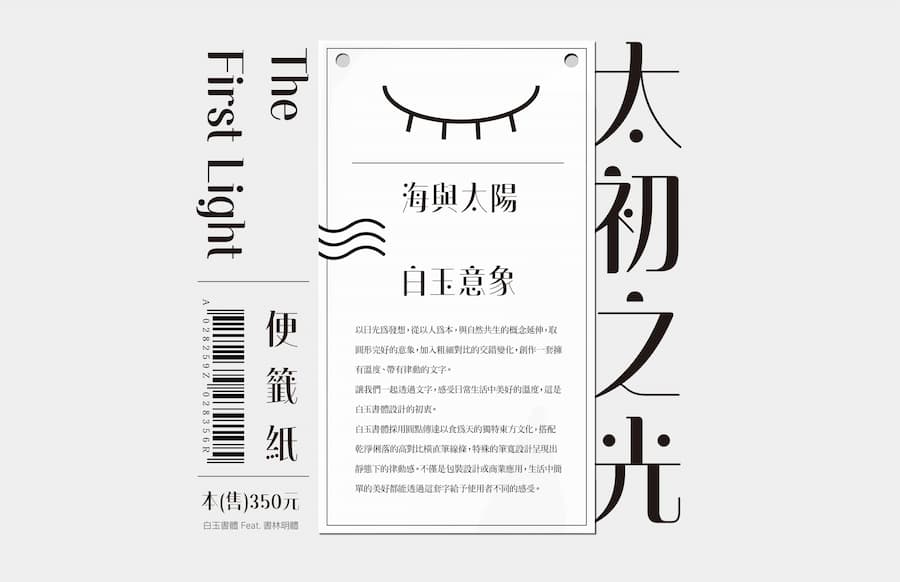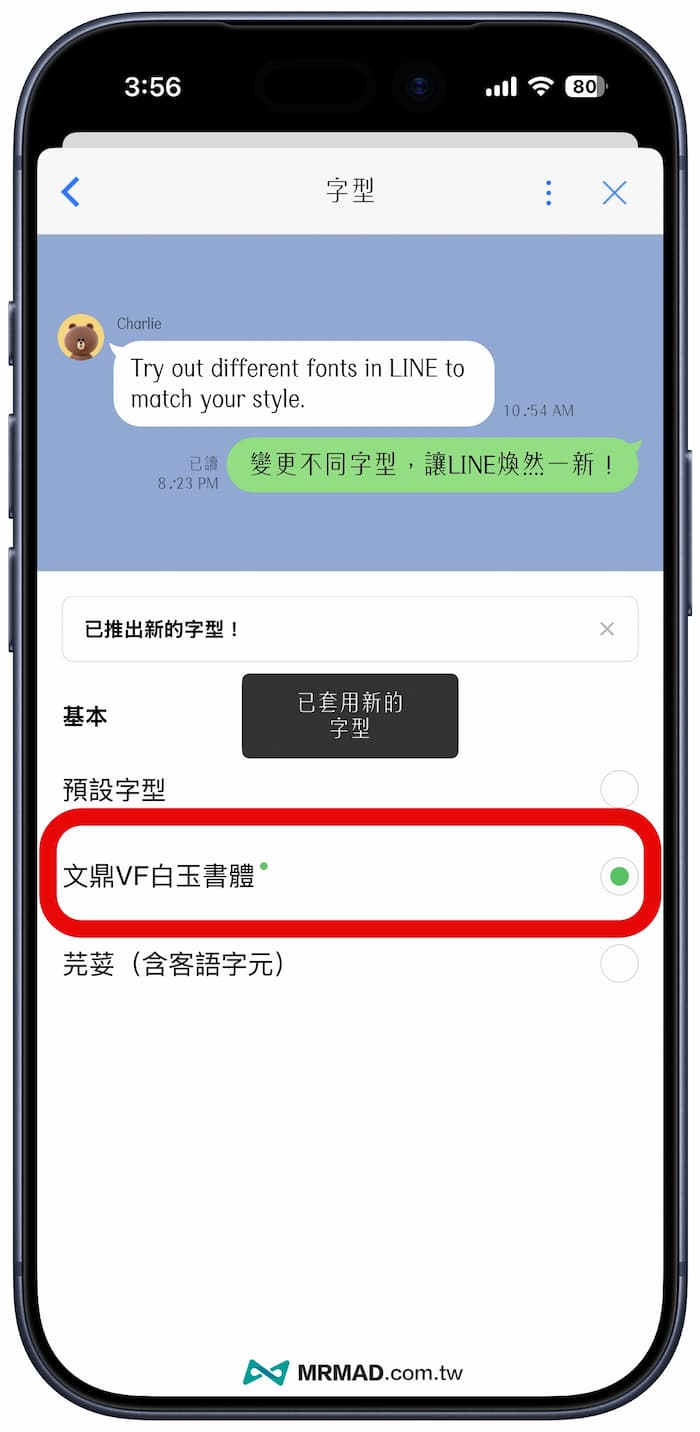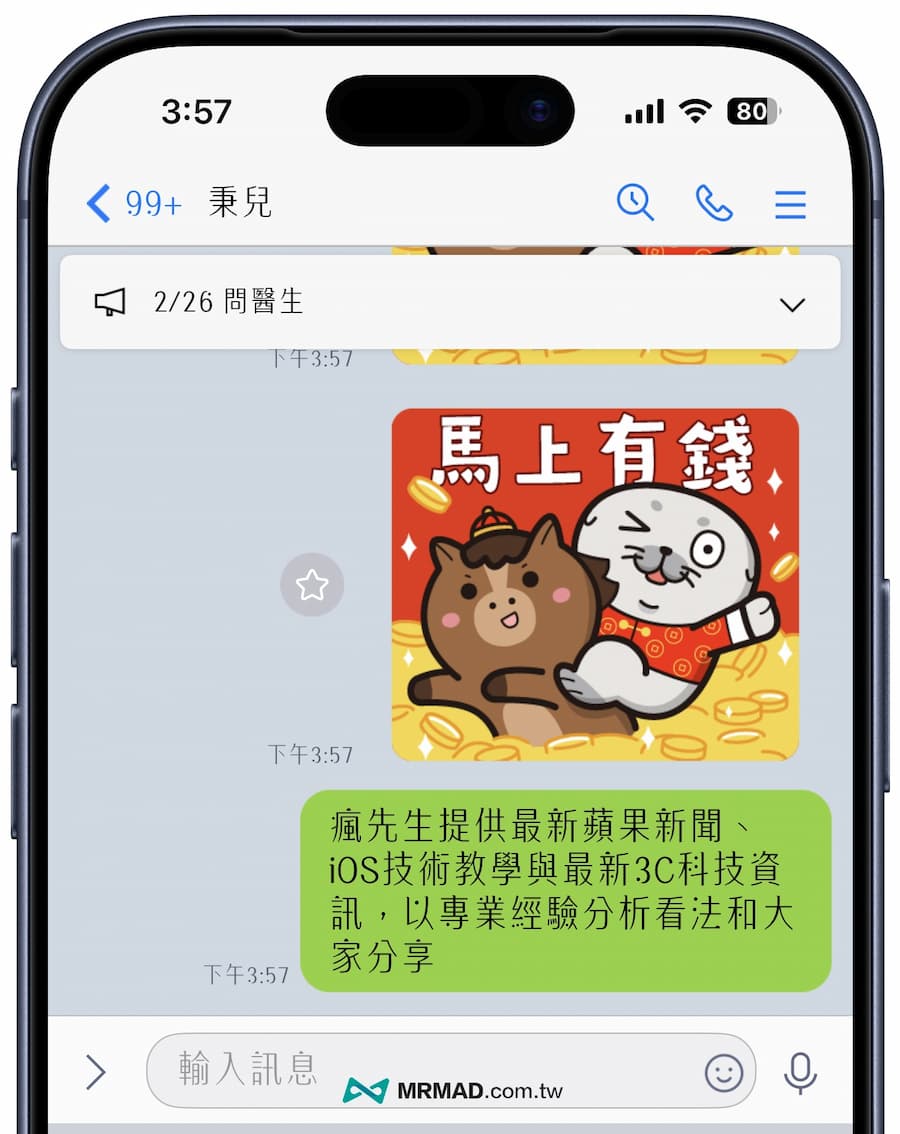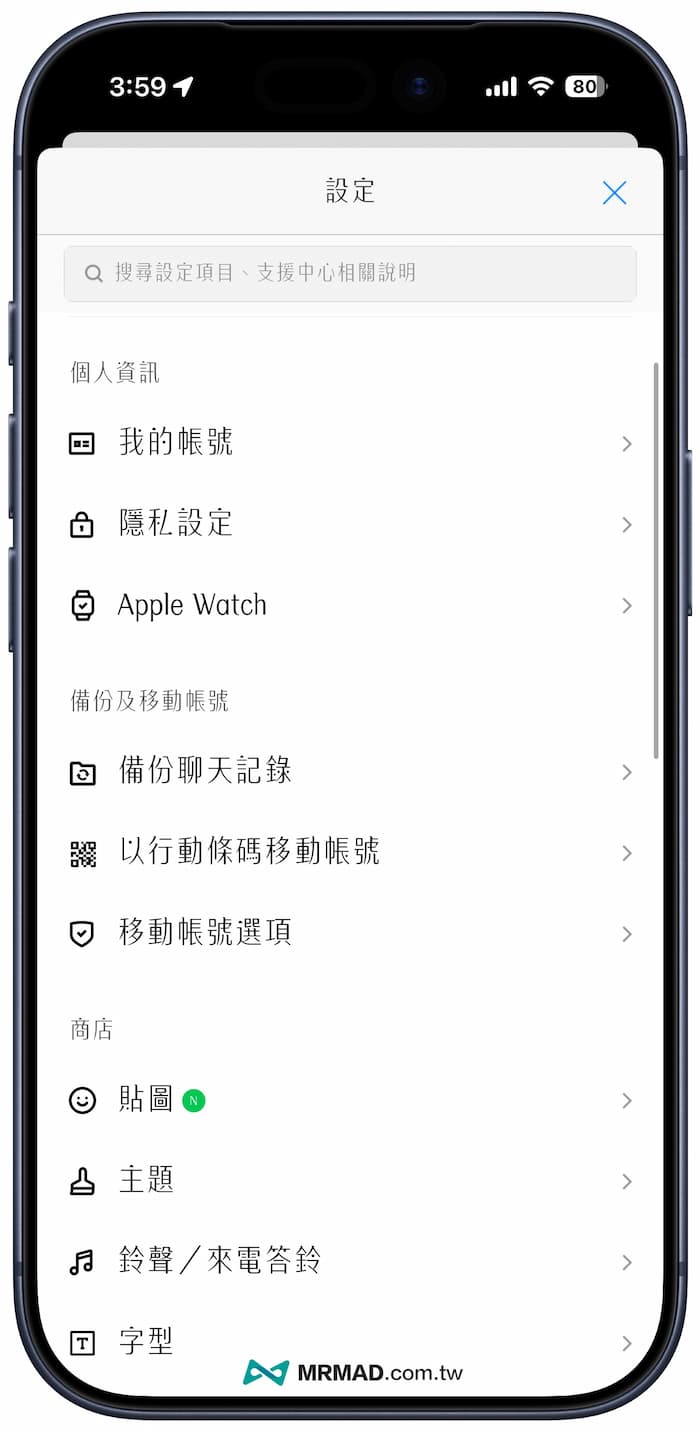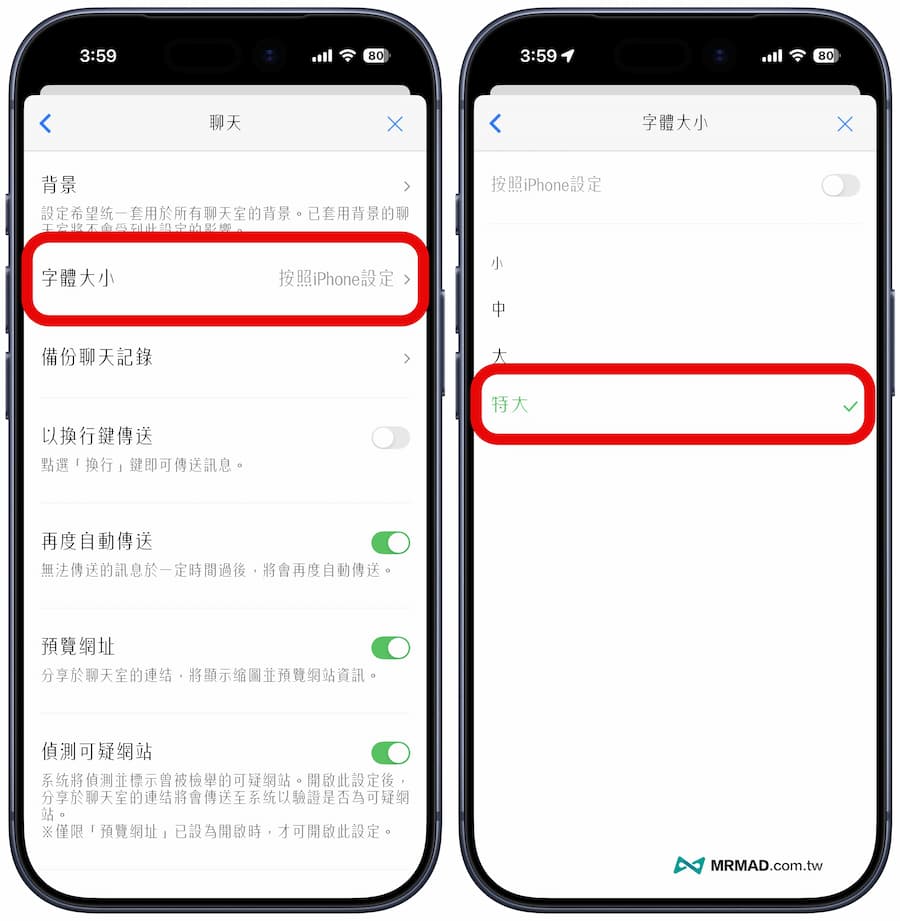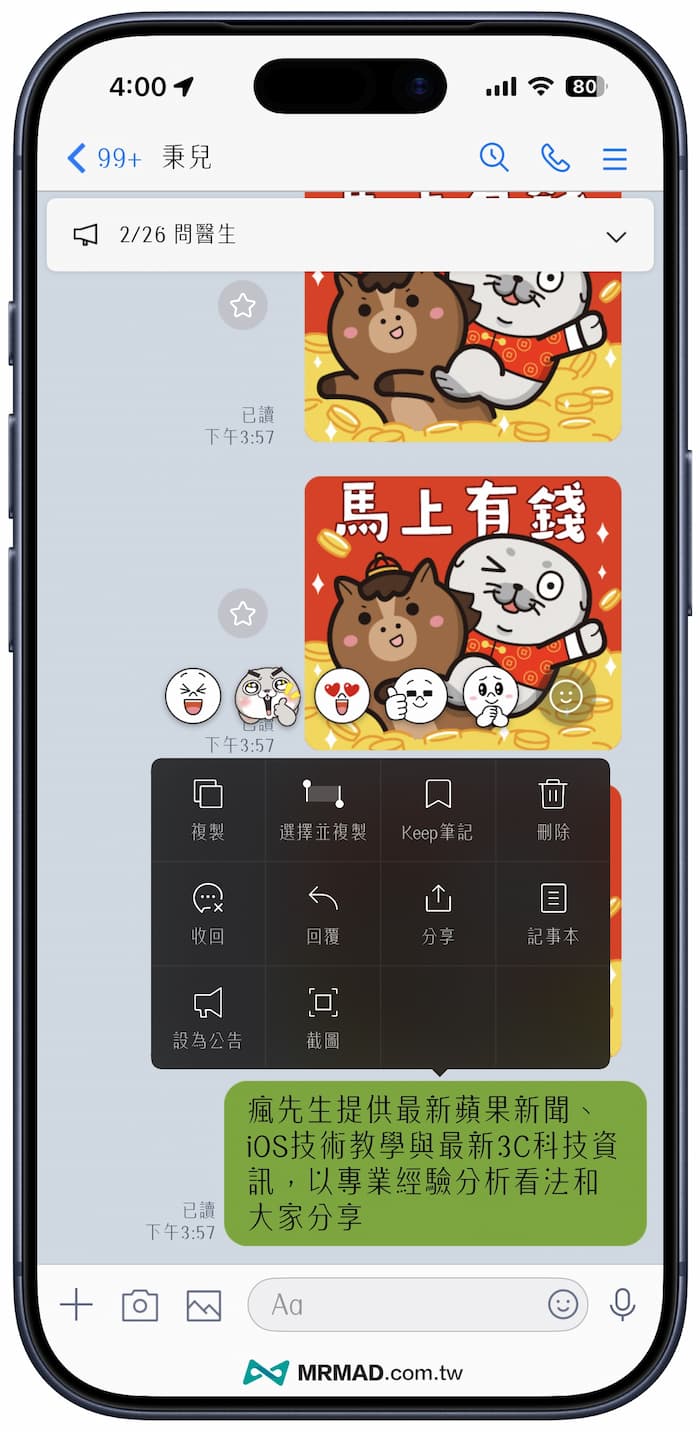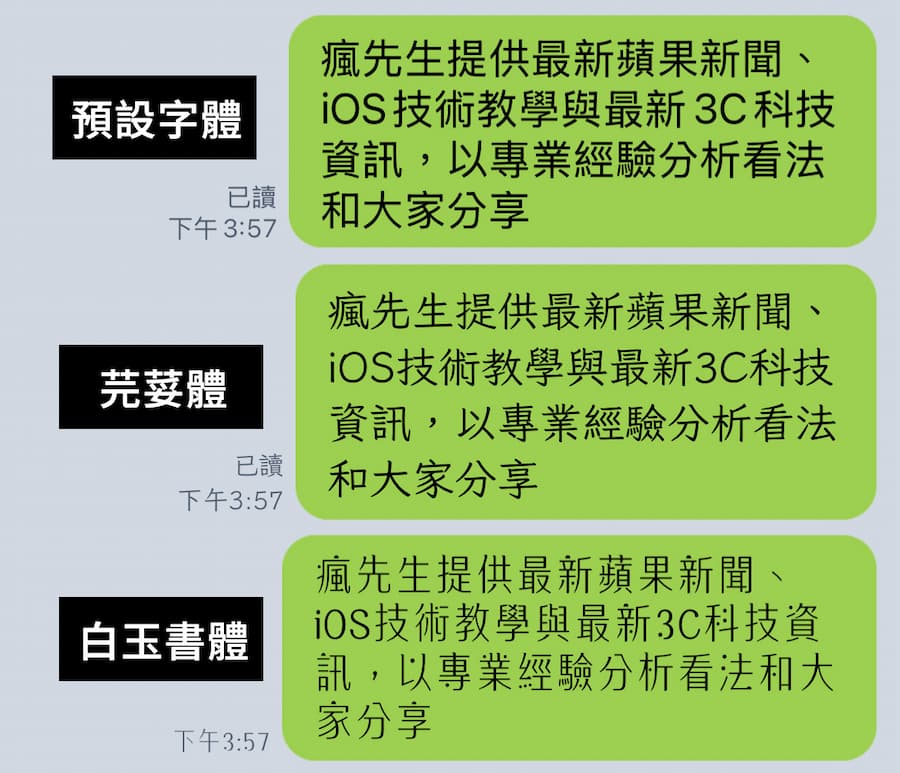
每天都在用的 LINE,看膩了預設字體嗎?LINE 官方近期在手機版悄悄釋出了第三款免費字型「文鼎白玉書體」!這款字體帶有濃濃的文青感與圓潤氣息,一推出就在 Threads 等社群引發網友熱烈討論,本文就來分享 LINE白玉書字體下載套用方法,讓你的 LINE 聊天室也能煥然一新!
LINE白玉書字體長怎樣?與預設LINE字型和芫荽體比較
目前 LINE 手機版內建共提供三種字型讓用戶自由切換,這次新增的白玉書體到底與預設和芫荽體有什麼不同?主要差異如下:
• 系統預設字體: 中規中矩,辨識度最高,適合所有情境與長輩使用。
• 芫荽體: 帶有手寫的溫度感,字跡端正優雅,是前一波爆紅的字體。
• 文鼎白玉書體: 這次的主角!字體整體偏細,筆畫橫直對比明顯,帶點圓潤的可愛感,風格非常清新文青。
白玉書字型設計理念是什麼?
「文鼎白玉書體」是由知名的文鼎字型公司操刀設計,主要是日光為發想,結合了以人為本、與自然共生的理念。
如仔細觀察它的筆畫,會發現它橫筆圓潤、直筆帶有線條修飾,而點的筆畫則是可愛的正圓形,這種高對比的粗細變化,讓文字在靜態中帶有一種律動感,替冰冷的手機螢幕注入了東方人文的溫暖氣息。
放大後的白玉書體不僅保留了圓潤的美感,還能大幅降低閱讀負擔,完美兼顧美觀與舒適度!